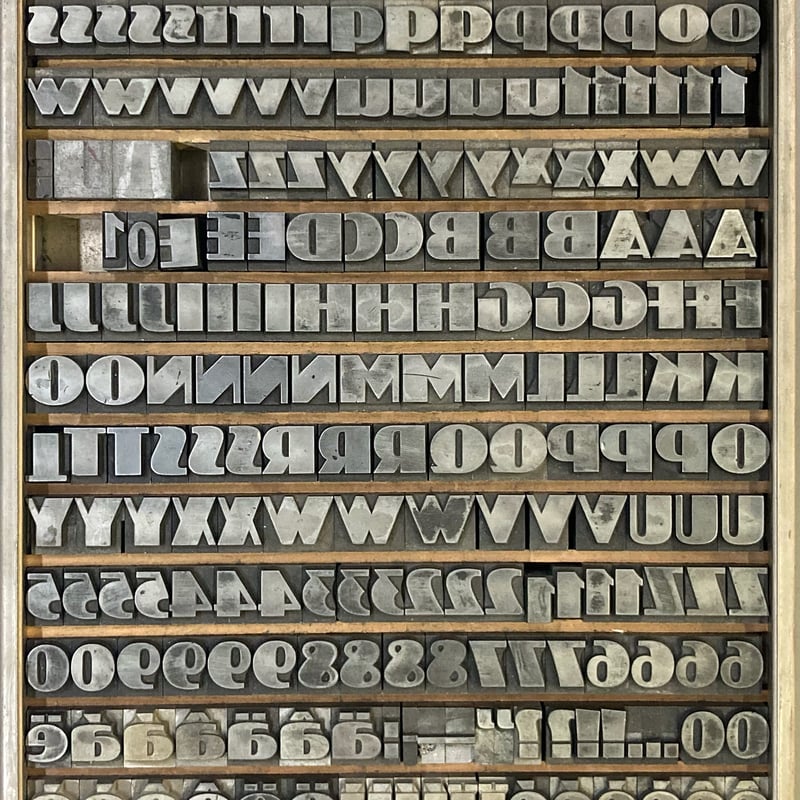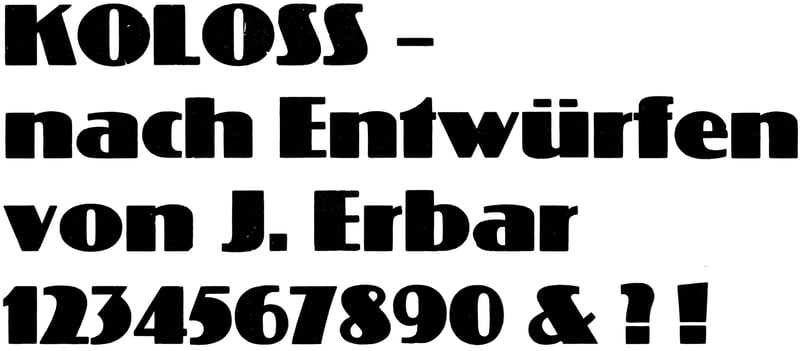
Koloss
Druckmuster mit Text «Koloss, 48pt»
Sans Serif, Display
Design
Jakob Erbar
Jahr
1923
Schriftgiesserei
Ludwig & Mayer
Wurde als extrafetter Begleiter zur Feder-Grotesk und als zeitgemässe Schrift für Werbedrucke angepriesen.